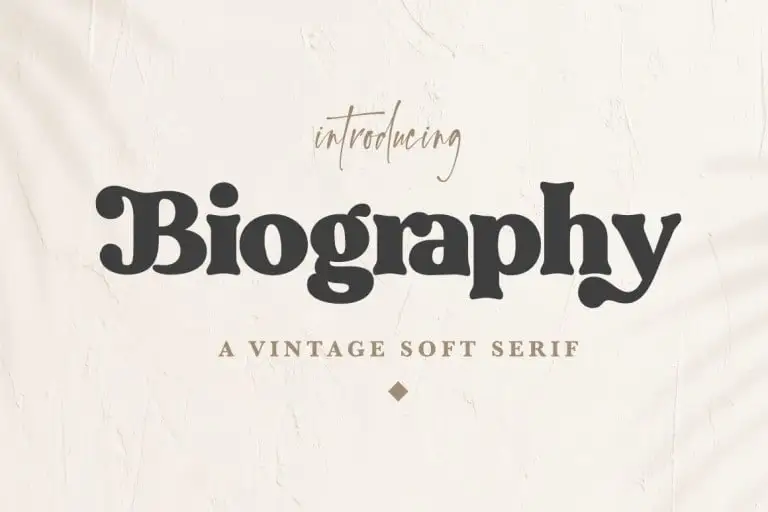
Biography Serif Font – Fonte Grátis
Biography Serif Font
A ‘Biography Serif Font’ é uma elegante serif vintage que promete se destacar em sua marca entre a concorrência. Esta fonte retrata momentos nostálgicos e atemporal, com suas curvas fortes criando um estilo retro vibrante. Com sua simplicidade clara e graça deslavada, ela atrai atenção e faz seu design ser notável. Este belo e elegante produto é uma escolha perfeita para quem busca dar ao branding um toque vintage. Desenvolvida pelo Silverdav Studio em 99designs, a ‘Biography Serif Font’ incorpora os elementos de curvas fortes que fazem esta fonte retrô e vintage, criando um estilo único capaz de chamar a atenção dos consumidores.